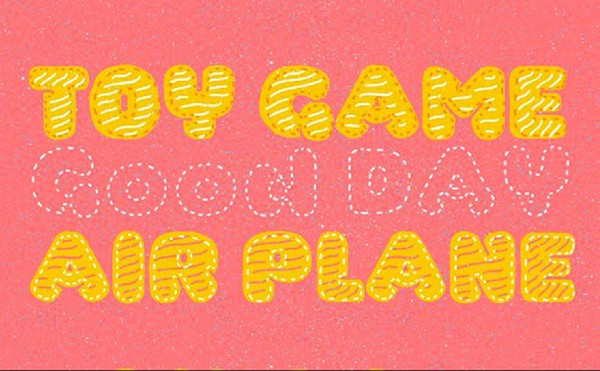
Trong cộng đồng hiện nay có rất nhiều font chữ đẹp với đa dạng phong cách, kiểu dáng cũng như hướng tới từng mục đích khác nhau. Với mục đích mong muốn thiết kế những tác phẩm truyện tranh, hoạt hình hay chỉ đơn giản là những tấm thiệp chúc mừng mang màu sắc đáng yêu, dễ thương. Vậy thì bài viết này là dành cho bạn, hãy tham khảo top những font chữ dễ thương mà FPT Arena sẽ giới thiệu cho bạn trong bài viết dưới đây nhé!
Font chữ việt hóa là gì ?
Không phải tất cả các font đều là tiếng Việt. Có nhiều phông chữ khác nhau trên thế giới và chúng được cung cấp ở mỗi quốc gia. Tất nhiên, chỉ có ngôn ngữ của quốc gia được hỗ trợ, vì vậy nếu bạn muốn sử dụng các font này bằng tiếng Việt thì cần phải việt hóa. Ở đây có thể hiểu đơn giản là các font tiếng Việt chính là dịch từ các font chữ nước ngoài vốn không thể diễn đạt tốt bằng tiếng Việt thành các nét thể hiện rõ ràng và hay hơn (thường là do lỗi dấu tiếng Việt).
Những lý do nên sử dụng font chữ việt hóa?
Do các ngôn ngữ khác nhau mà có cấu trúc bảng chữ cái khác nhau nên việc xem các tài liệu tiếng Việt sử dụng phông chữ tiếng nước ngoài thường dẫn đến lỗi được gọi là lỗi phông chữ. Nguyên nhân là do các phông chữ này không tìm được ký tự phù hợp với các ký tự tiếng Việt có dấu (ký tự có dấu – một trong những nguyên nhân phổ biến nhất gây ra lỗi phông chữ) nên chúng sẽ tự động tìm và thay thế ký tự bằng cách gán bất kỳ ký tự nào thay thế các ký tự bị thiếu.
Đặc biệt trong thiết kế, việc sử dụng phông chữ không rõ ràng có thể dẫn đến trình bày nội dung của bạn kém, khiến khán giả khó đọc hoặc hiểu sai nội dung của bạn, do đó làm sai lệch hiệu quả, kết quả của sản phẩm thiết kế, thậm chí cả người đọc và có thể gây phản đối từ xã hội và cộng đồng.
Đối với các văn bản quy phạm pháp luật, các lỗi chính tả cần tránh do tính nghiêm túc, rõ ràng và minh bạch của các văn bản này. Các lỗi chính tả rõ ràng khó đọc trong văn bản làm cho văn bản dường như không có tác dụng. Vì vậy, bạn nên sử dụng phông chữ tiếng Việt để văn bản và nội dung của bạn được trình bày tốt nhất đến người đọc.
Top những font chữ dễ thương mà bạn nên tham khảo sử dụng cho thiết kế của mình.
Các phông chữ được đề xuất dưới đây dựa trên mức độ phổ biến của chúng trong thiết kế. Sau khi nghiên cứu hơn 500 hình ảnh thiết kế trong thư viện ảnh trên datadesignsb.com, thấy rằng các nhà thiết kế Việt Nam sử dụng thường xuyên các phông chữ này.
Font Rukola
Đây là một trong những font chữ phù hợp nhất với người Việt Nam, tất cả các ký tự đều được viết tay bằng tiếng Việt, quen thuộc và dễ đọc. Phông chữ Rukola là một loại phông chữ brush script hỗ trợ nhiều ngôn ngữ và bộ ký tự phong phú. Các lựa chọn thay thế OpenType và Swash độc đáo của phông chữ cho phép bạn cảm nhận được sự mềm mại và linh hoạt của phông chữ này. Font Rukola phù hợp để đóng gói mẫu, tạp chí, ấn phẩm …
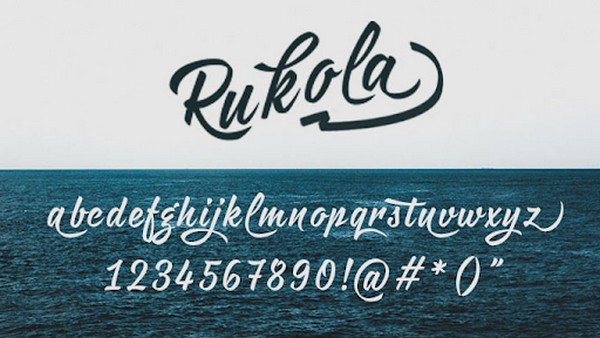
Font Brandon
Một trong những mẫu font tiếng Việt tốt nhất hiện nay, với nhiều biến thể. Phông chữ Brandon có tính chất ấm áp và linh hoạt, phù hợp với nhiều nhu cầu khác nhau, chẳng hạn như được sử dụng trong nhiều lĩnh vực như hiển thị văn bản trên các trang web, phông chữ cho sách trực tuyến, và thiết kế. Phông chữ phổ biến dễ tìm thấy ở mọi nơi.
Font Chomp
Đây là một thiết kế phông chữ khá dễ thương và đặc biệt có thể tải xuống miễn phí. Font Chomp được phát triển bởi nhà thiết kế gốc Bayley Suckling. Chomp có đặc điểm là ít vui nhộn hơn các phông chữ khác, tạo cho người xem cảm giác thoải mái và vô tư, không cầu kỳ. Mẫu font này rất phù hợp cho các mục đích thương mại và các ấn phẩm thiết kế tạp chí nghiêm túc, chuyên nghiệp.
Font Ariel Signature
Viết những cuộc phiêu lưu của riêng bạn với phông chữ chữ ký Ariel tuyệt đẹp. Một kiểu chữ viết tay độc đáo bắt chước chữ viết tay thật, phông chữ này có các nét đứt và bản chất tối giản. Bạn có thể sử dụng nó cho đồ họa truyền thông xã hội hoặc tạo logo của riêng bạn.
Font Stantic Typeface
Được tạo ra với thiết kế logo, kiểu chữ của Stantic có tác động rất lớn đến khán giả của bạn. Với phong cách tương lai bao gồm các chữ cái dài và nét đậm, phông chữ này hoàn hảo cho văn phòng phẩm, biển quảng cáo hoặc bộ nhận diện thương hiệu.
Font Pixie Ring
Thêm một font chữ rất được hầu hết các cặp đôi yêu thích để thiết kế tặng cho nửa kia. Phông chữ Ring Pixie không chỉ được tô điểm bằng hình trái tim cực dễ thương trên đầu mà bạn còn có thể thêm những chi tiết dễ thương như kim cương, vương miện, ngôi sao… Bạn hoàn toàn có thể thoải mái lựa chọn theo sở thích của mình đặc biệt phông chữ này hoàn toàn có sẵn và miễn phí.
Font Apple Juice
Một số phông chữ sans-serif có thể hơi cứng về phong cách, nhưng phông chữ Apple Juice siêu dễ thương này là một ngoại lệ. Thiết kế mới lạ mang cảm giác vui nhộn và bắt mắt khiến kiểu chữ này được dùng làm tiêu đề bìa sách thiếu nhi. Kết hợp font chữ cùng màu sắc yêu thích của bạn để nâng tầm sáng tạo thiết kế lên một tầm cao mới.
Lời kết